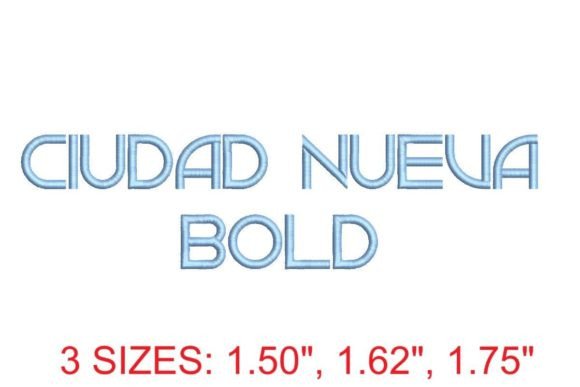
Ciudad Nueva Bold Embroidery Font
Jika Anda mencari aset berkualitas tinggi seperti Ciudad Nueva Bold Embroidery Font, paket premium ini adalah pilihan fantastis untuk proyek kreatif Anda.
Build Quality & Specifications
Who Is This Best For?
Baik Anda membuat produk POD (Print on Demand), undangan pernikahan, atau grafis media sosial, Ciudad Nueva Bold Embroidery Font adalah pilihan yang sangat ideal.